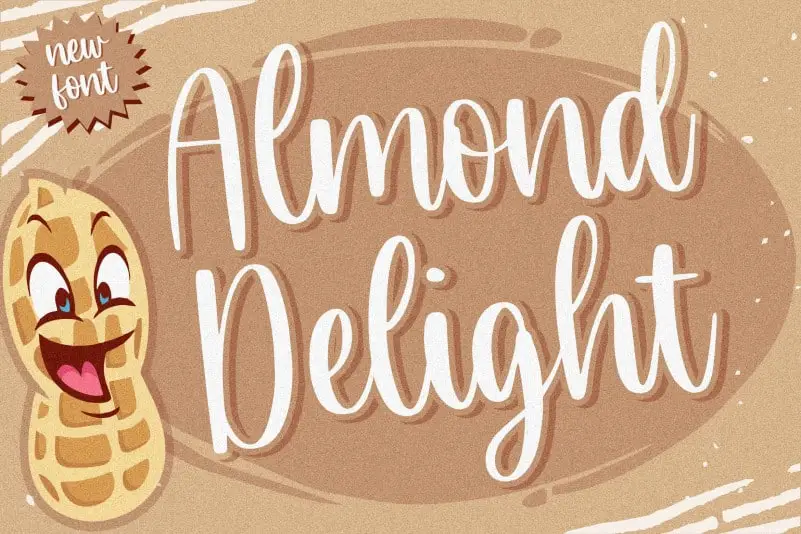
Almond Delight Handwritten Font – Download Grátis
A “Almond Delight Handwritten Font” é uma seleção única que combina a elegância natural do traço manual com uma leveza poética, perfeita para estilos criativos e artísticos. Suavemente suave e repleta de delicadeza, esta fonte torna-se o alicerce para ideias de design emocionantes e arredondados em qualquer aplicação. Perfeito tanto para editoriais amigáveis ao público quanto para embalagens de produtos sofisticadas, é uma escolha excepcional que expressará sua mensagem com elegância no meio da multidão. A fonte também se destaca na criação de designs para casamentos e publicidade, dando um toque único em qualquer projeto.